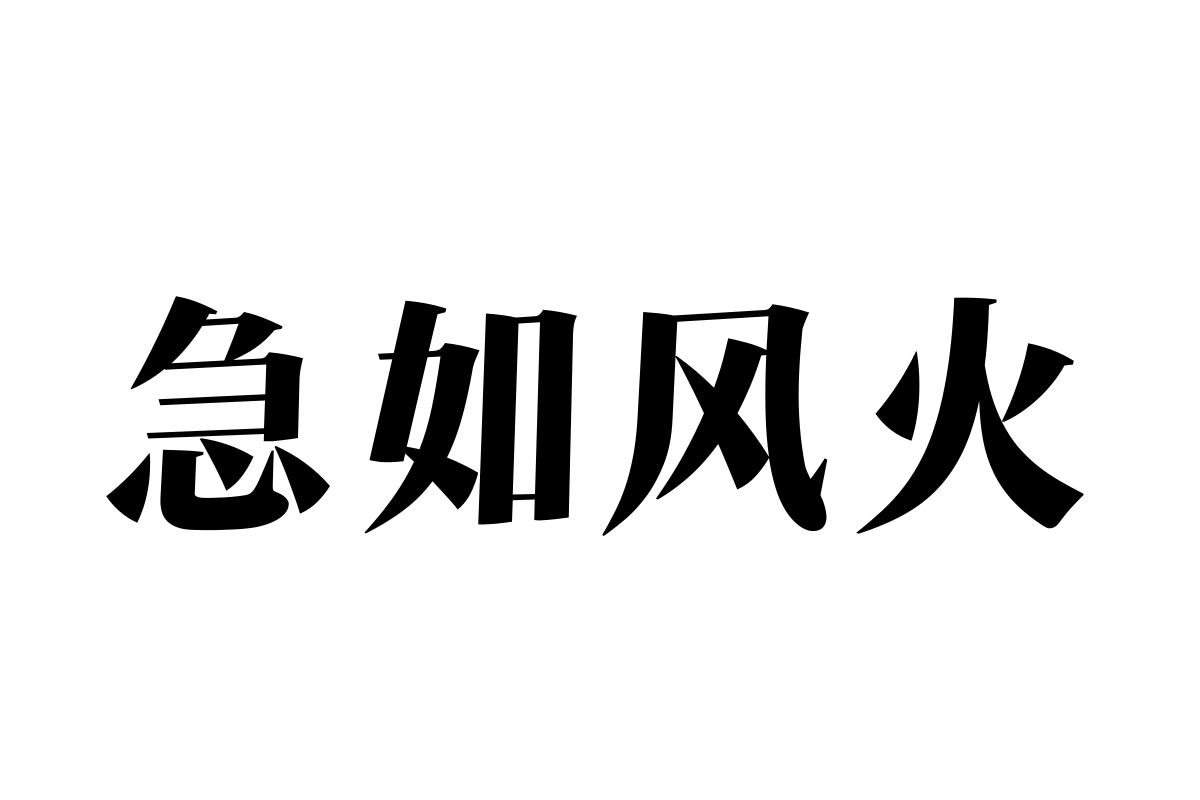
汉仪瑞意宋I_95W是一款由汉仪公司设计的一款中文字体,主要用于商业和正式的文档中。这款字体的特点是字形规整,笔画清晰,适合用于印刷品和电子屏幕上的文字显示。
汉仪瑞意宋I_95W的特点如下:
1. 字形规整:该字体的字形规整,笔画清晰,易于阅读和识别。
2. 笔画流畅:该字体的笔画流畅,无明显的断笔和连笔现象,使得文字看起来更加美观。
3. 适应性强:该字体适用于多种场景,包括商业广告、企业宣传、产品说明书等。
总的来说,汉仪瑞意宋I_95W是一款实用且美观的中文字体,广泛应用于各种商业和正式的文档中。